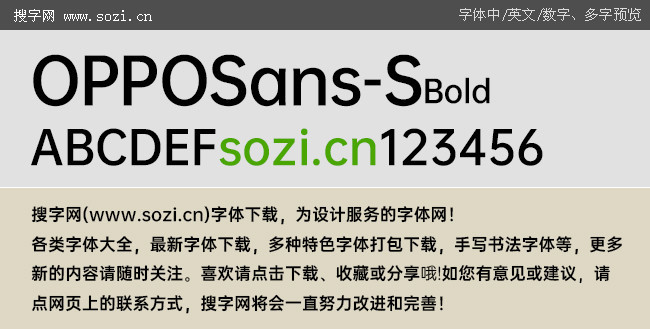
OPPOSans-S-B字體
搜字網(wǎng)給大家提供一款OPPOSans-S-B中文字體下載,OPPOSans-S-B是OPPO全新的品牌字體,字體采用了全新骨架,中宮自然舒適,更加挺拔優(yōu)雅;簡(jiǎn)化筆畫(huà),把握更多細(xì)節(jié)處理,去除出腳,更加干凈。它針對(duì)移動(dòng)端做了很多像素級(jí)的優(yōu)化,長(zhǎng)時(shí)間閱讀也不累。適用于大標(biāo)題、包裝設(shè)計(jì)、海報(bào)設(shè)計(jì)等應(yīng)用。